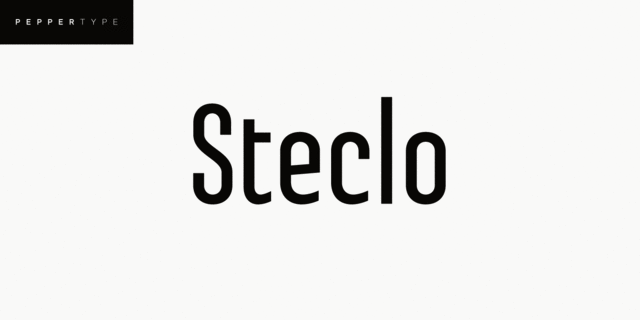
Это полузакрытый узкий акцидентный гротеск с ярко выраженным техническим характером. Поставляется в 9 весах от тонкого до сверхжирного с соответствующими наклонными начертаниями. Steclo имеет широкую языковую поддержку, включая латиницу и кириллицу. Шрифт разработал Олег Лищук в 2021 году.
тонкий, стройный, худой, ровный, высокий, городской, узкий, техничный, качественный, точный, четкий, хрупкий, прозрачный, современный, интересный, оригинальный, динамичный, гладкий, лаконичный, неоновый, ясный, чистый, серьезный, чертежный, инженерный, твердый, громкий, уверенный, заметный, амбициозный, важный, мотивирующий, убедительный, крепкий, сильный, техногенный, железный, надежный, стальной, стабильный, автоматический, индустриальный, практичный, доступный, урбанистический, крутой, кинематографичный, взрослый, монотонный, устойчивый, архитектурный, рабочий, ответственный, решительный, тяжелый, суровый, броский, яркий, выразительный, активный, спортивный, смелый, мощный, острый